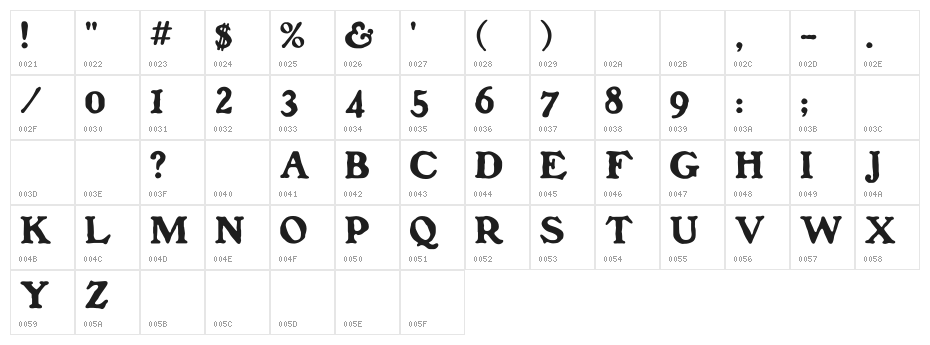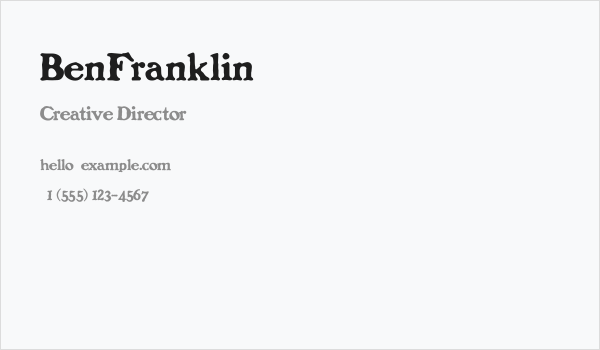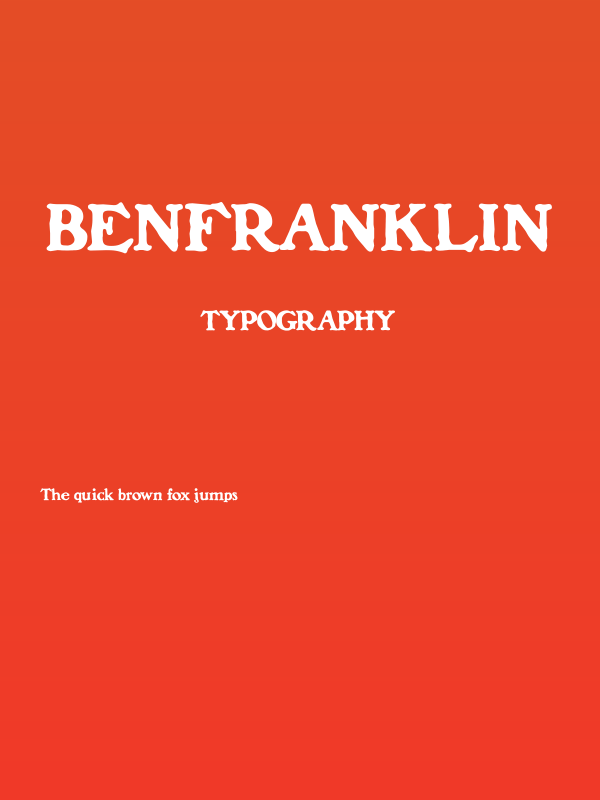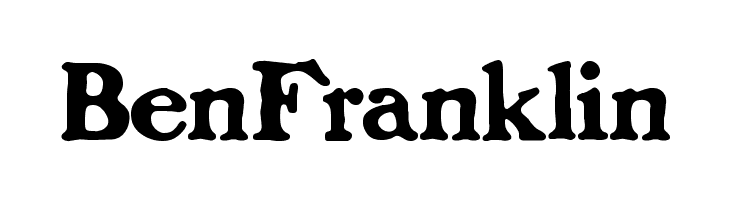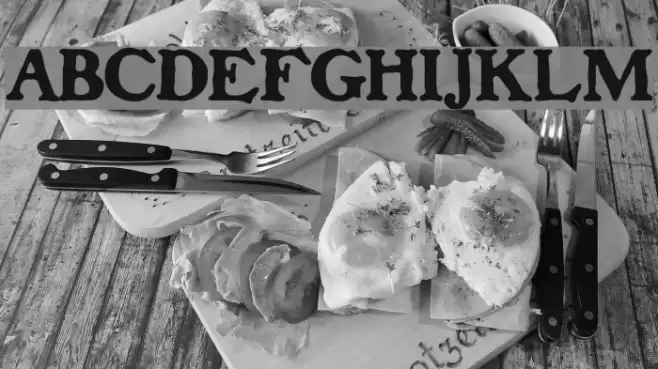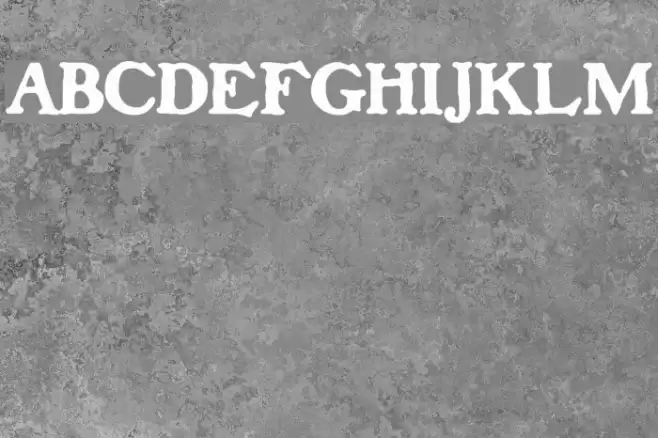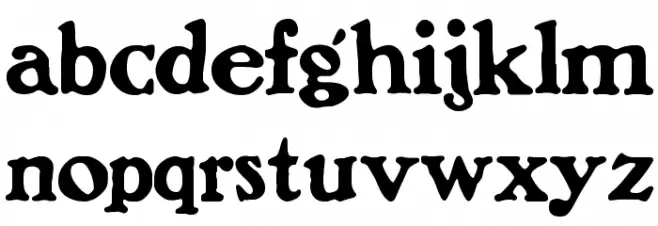
BenFranklin Font
| Projets proposés | Ideal for projects that require a historical or vintage touch, such as posters, book covers, or branding for traditional products. |